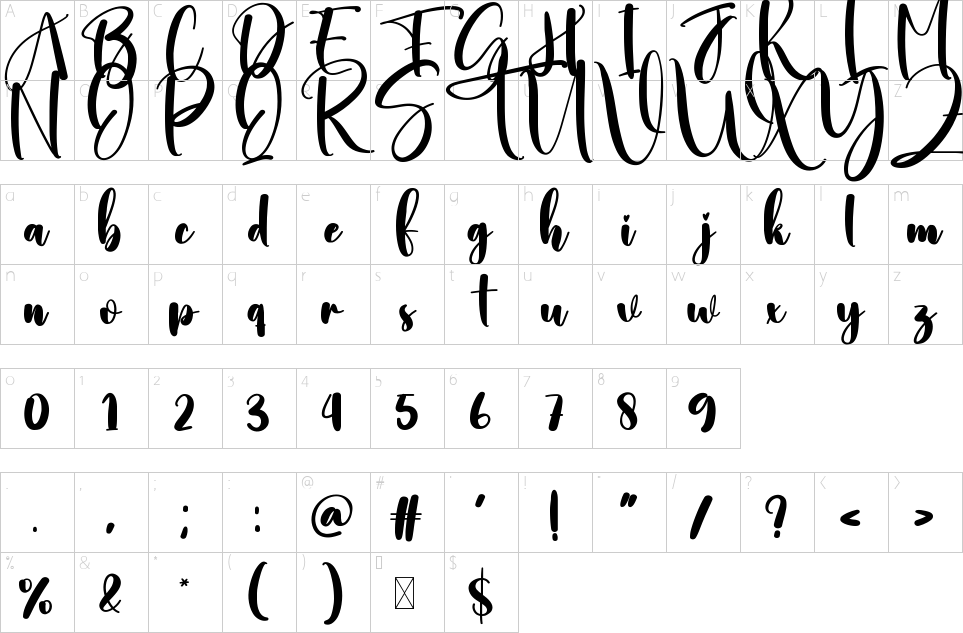
Pinky Font | 1001 Free Fonts – Fonte Grátis
Descubra a encantadora Pinky font em nosso catálogo de fontes gratuitas. Desenvolvida por scratchones, a Pinky font está disponível tanto para uso em Windows quanto em Mac. Esta fonte delicada e única foi projetada para dar um toque especial a suas criações digitais. Com um design criativo e versátil, a Pinky font é uma excelente opção para aqueles que desejam dar um toque especial em seus trabalhos de design, seja para o texto, os gráficos ou até mesmo em pequenos detalhes. Com mais de 500 downloads, a Pinky font é uma fonte de qualidade que merece ser explorada. Seja para um projeto pessoal ou profissional, a Pinky font é uma fonte que certamente irá impressionar. Não perca mais tempo, baixe a Pinky font agora e descubra o prazer de usar uma fonte única e criativa.